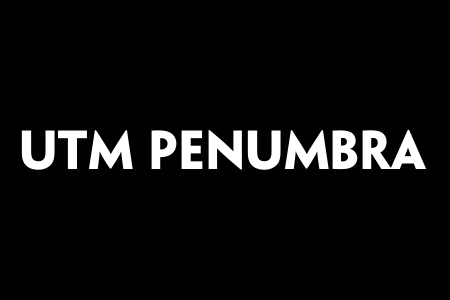
Font UTM Penumbra Việt Hoá
UTM Penumbra là một lựa chọn độc đáo trong thiết kế, nổi bật với phong cách hiện đại và đầy cá tính. Được phát triển bởi UTM, font chữ không chân này mang đến sự kết hợp tinh tế giữa các đường nét mạnh mẽ và mềm mại, tạo nên một cảm giác vừa năng động vừa thanh lịch. UTM Penumbra rất phù hợp cho các dự án đòi hỏi sự sáng tạo và nổi bật, chẳng hạn như thiết kế logo, tiêu đề, hay các ấn phẩm quảng cáo. Với tính linh hoạt và thẩm mỹ cao, phông chữ này giúp bạn tạo nên những sản phẩm ấn tượng và khác biệt.